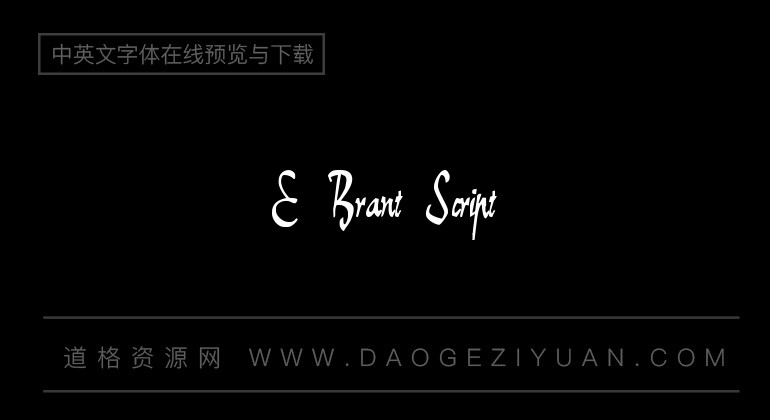
E-Brant Script 字体是一种手写风格的字体,具有华丽、流畅和优美的特点。该字体的笔画流畅自然,其中的每个字母都有独特的特点,使得它们在排版时具有高度的可识别性和美感。 E-Brant Script 字体非常适合应用于手写信件、卡片、海报、广告、标志、包装等等需要表现个性和温馨的场合。它的设计灵感来源于自然风景、艺术等元素,带有一定的时尚感和现代感。 该字体包含了大写字母、小写字母、数字和标点符号等多种字符,可用于多种语言的排版。它是一款非常实用的字体,可以让你的作品更具创意性和美感。内容介绍
E-Brant Script是一款非常不错的手写艺术字体,具有很好的视觉感,适合于文化类的宣传设计、商业类品牌的广告和产品包装设计以及个性化文字排版等较多场景。